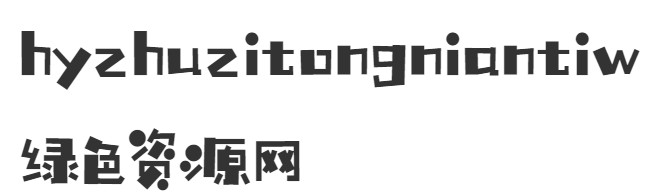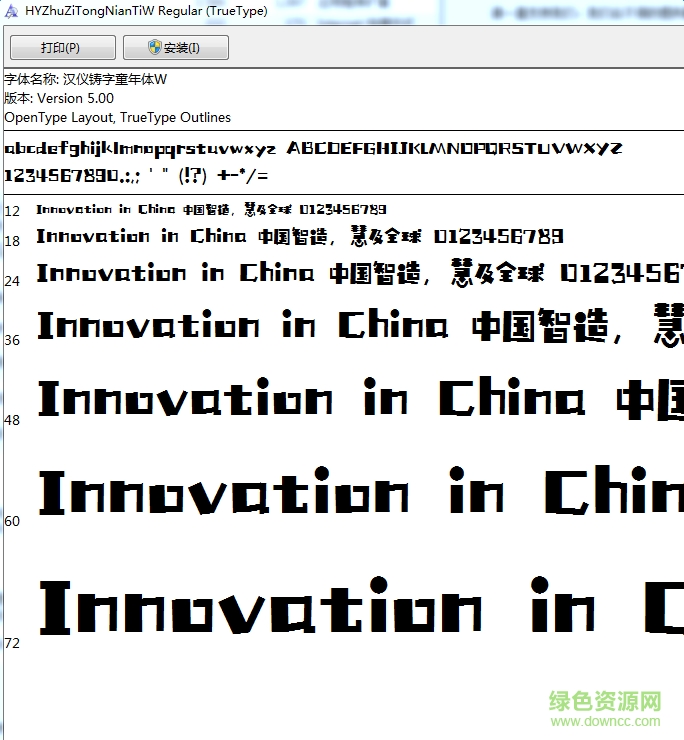
hyzhuzitongniantiw字體又叫漢儀鑄字童年體w regular字體,是一款充滿童趣的可愛字體,粗細(xì)相間,線條過(guò)渡自然,適合用在動(dòng)漫海報(bào)、包裝設(shè)計(jì)等各個(gè)方面,歡迎大家免費(fèi)下載!
該字體線條粗壯,
1.整體效果非常的出眾,并且字庫(kù)完整;
2.字形設(shè)計(jì)的風(fēng)格比較適合大字體行業(yè)的設(shè)計(jì)需求;
3.字形呈卡通風(fēng)格可用于藝術(shù)設(shè)計(jì)、包裝印刷;
4.可以在設(shè)計(jì)游戲?qū)υ挼臅r(shí)候使用。